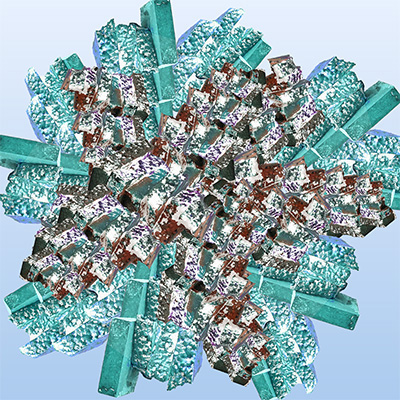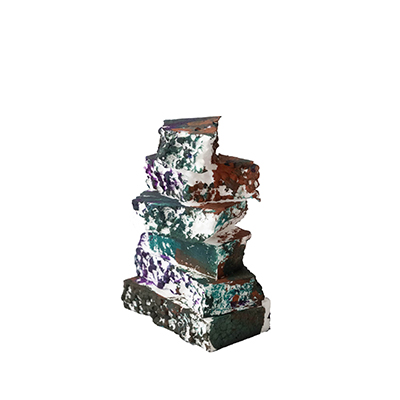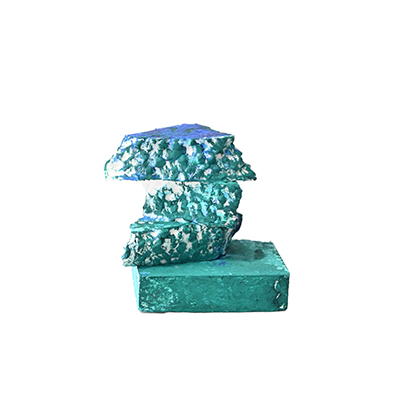
余白
残された白が描く、雪の息吹
Artist日山りさ
Designerジャンウェイ
Organizationワークささはた
花火!(日山りさ)
日山さんが制作した立体をもとにしています。あえて塗り残した発泡スチロールの白が、雪の結晶のように、見る人に強い印象を与えました。(ジャンウェイ)
施設の廃材から輝くアートが生まれました。(ワークささはた)